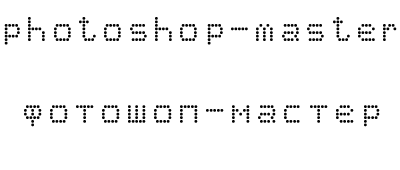
Кажется, что шрифт простой, но это очень тонкая мысль, не везде его можно использовать...но за задумку однозначно +.
Вау, для обработки исходников подойдет :D
точечки точечки:)))
Я бы сказал не струйного принтера, а матричного! Для абстракции очень хороший шрифт!
А если быть точнее, то это матричный принтер.